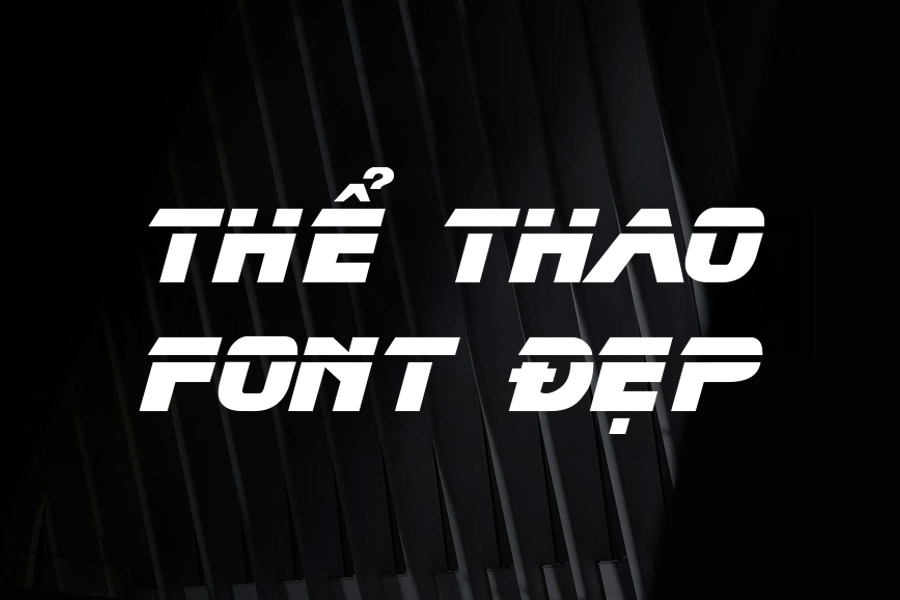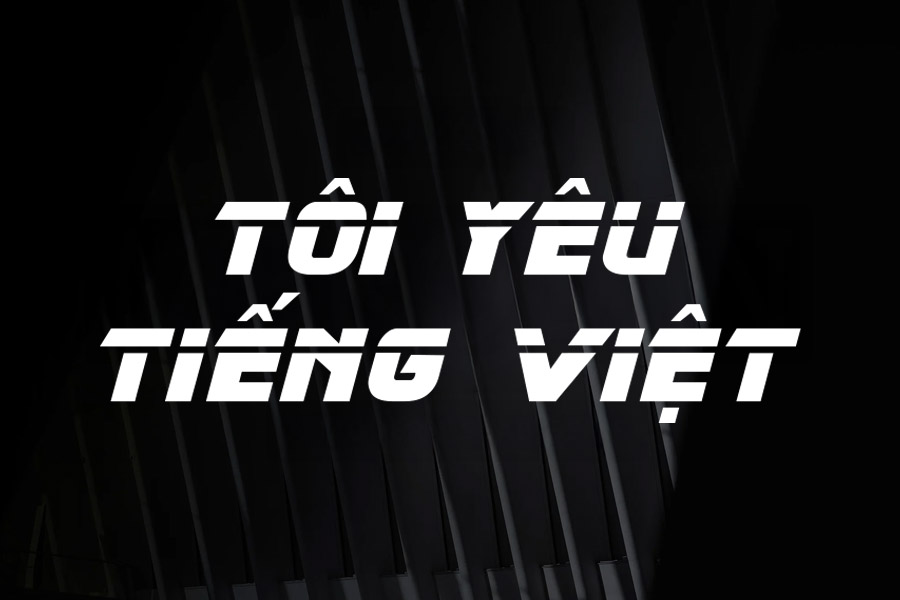
Tải miễn phí - SVN Blade Runner Việt hóa cho lĩnh vực thể thao mạnh mẽ
Tác giả Phil Steinschneider
Việt hóa Team SVN
Bạn đang tìm kiếm một font chữ mạnh mẽ và khác biệt cho thiết kế poster, banner công nghệ hoặc thương hiệu thể thao cá tính? Hãy khám phá SVN-Blade Runner Việt hóa – bộ font chữ thể thao đậm chất cyberpunk với đường nét sắc lạnh, lấy cảm hứng từ bộ phim viễn tưởng kinh điển Blade Runner.
Giới thiệu font chữ SVN-Blade Runner Việt hóa
SVN-Blade Runner Việt hóa là phiên bản được Việt hóa đầy đủ từ font chữ Blade Runner Movie Font, do nhà thiết kế Phil Steinschneider phát triển. Kiểu chữ này tái hiện hoàn hảo phần chữ xuất hiện trong tiêu đề phim Blade Runner (1982) và Blade Runner 2049, mang đậm phong cách tương lai – kỹ thuật số.
Phiên bản SVN-Blade Runner Việt hóa được thực hiện bởi SVN – đơn vị chuyên Việt hóa các bộ font chuẩn Unicode, đảm bảo hiển thị tiếng Việt đầy đủ, không lỗi dấu và sắc nét trong mọi thiết kế.
Vì sao SVN-Blade Runner là font chữ thể thao lý tưởng?
Không chỉ là font chữ cyberpunk, SVN-Blade Runner Việt hóa còn rất phù hợp với thiết kế thể thao nhờ:
• Đường nét đậm, dứt khoát và hình khối rõ ràng, tạo cảm giác tốc độ và năng lượng
• Kiểu dáng góc cạnh, toát lên sự khỏe khoắn, phù hợp với thương hiệu thể thao mạnh mẽ
• Hiệu ứng chuyển động, thích hợp với các bộ môn như eSports, đua xe, gym, bóng rổ, bóng đá…
Dù là poster sự kiện thể thao, logo đội tuyển hay banner chương trình thể hình, SVN-Blade Runner Việt hóa đều dễ dàng tạo được điểm nhấn riêng biệt và ấn tượng mạnh thị giác.
Tính năng nổi bật
• Font chữ đậm và cá tính, thiết kế theo phong cách sci-fi
• Hỗ trợ đầy đủ tiếng Việt có dấu, chuẩn Unicode
• Hoạt động tốt trong tiêu đề, logo, poster, hoặc headline cần sức mạnh thị giác
• Dễ ứng dụng trong các lĩnh vực: công nghệ, thể thao, giải trí, sự kiện
Ứng dụng của SVN-Blade Runner Việt hóa
Font chữ này được cộng đồng designer yêu thích nhờ tính đa năng, có thể dùng cho:
• Poster phim, banner game
• Logo thương hiệu thể thao, đồ gym, thể hình
• Giao diện app công nghệ, startup AI